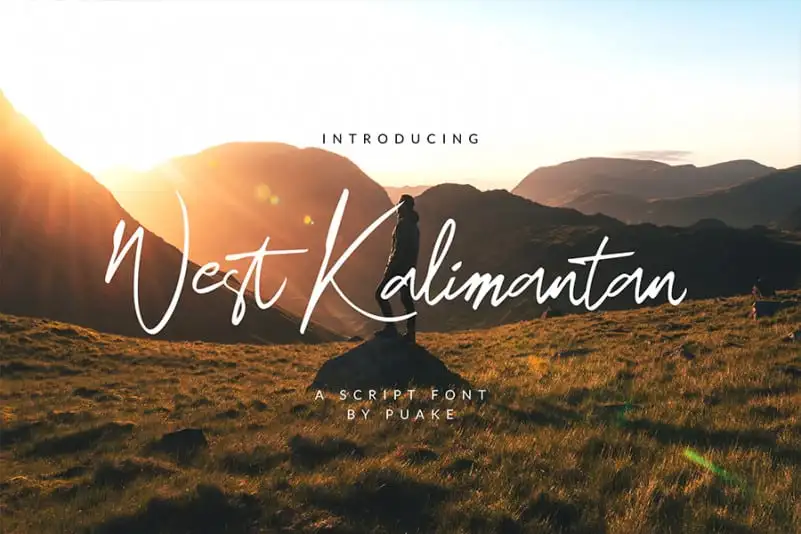
West Kalimantan Script Font – Download Grátis
A West Kalimantan Script Font é uma opção perfeita para os designers que procuram uma fonte com um estilo sofisticado e autêntico. Com seus traços arredondados únicos e sua fluida escrita, esta fonte tem tudo o que você precisa para criar designs irresistíveis. Perfeita tanto para t-shirts quanto para posters ou marcas de marca, ela oferece 50 ligaturas e suporte multilingue, tornando-a versátil para diversas aplicações. Seja a próxima camiseta personalizada, o próximo mural publicitário ou a identidade visual da sua empresa, essa fonte irá fazer você se destacar no mundo de design digital. Com um design natural e envolvente, certamente será uma escolha inteligente para qualquer projeto que deseje transmitir elegância e sofisticação.